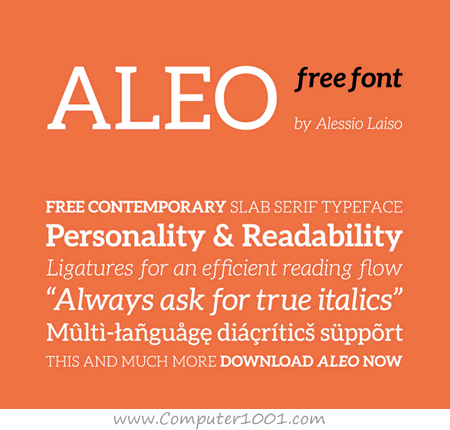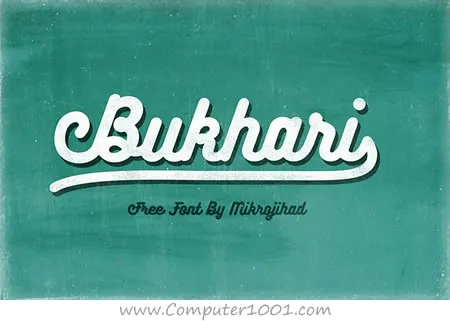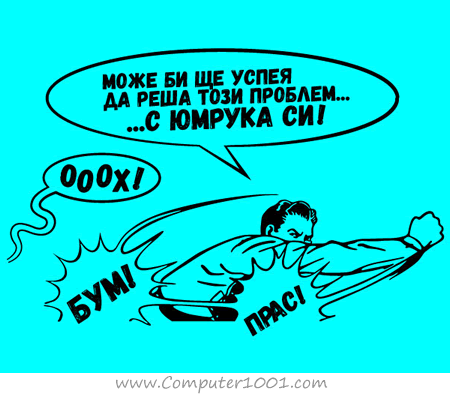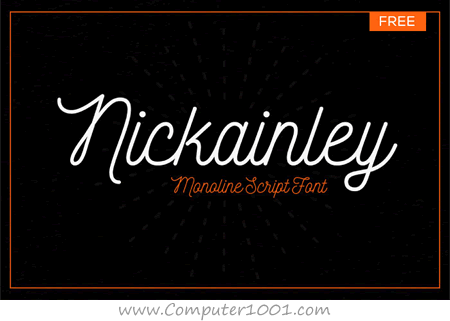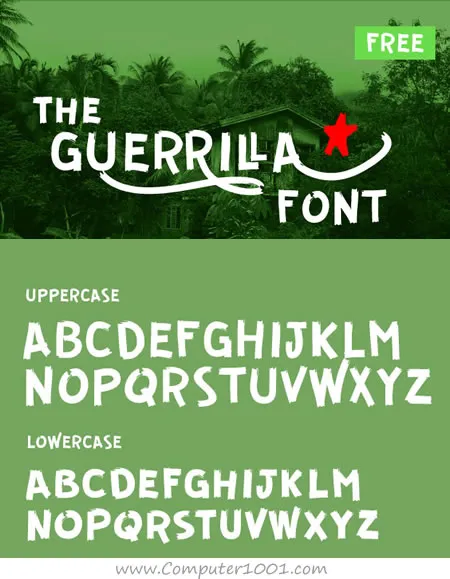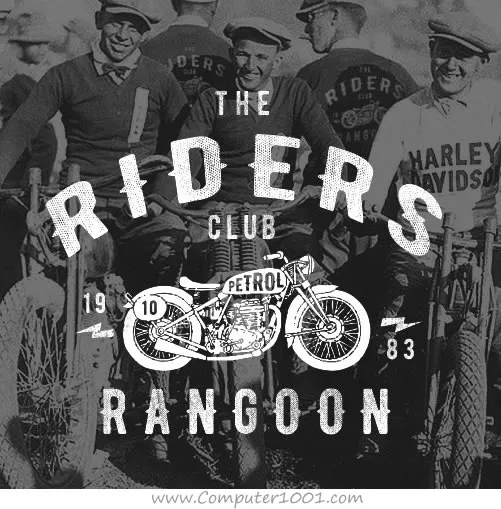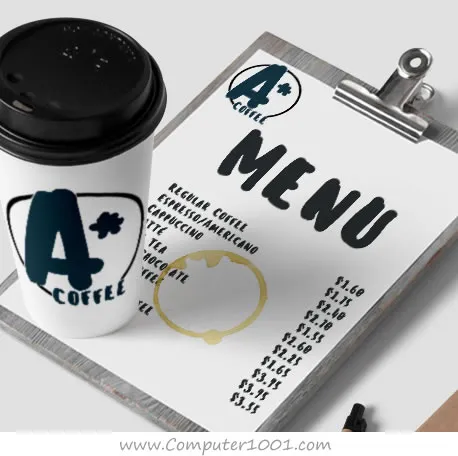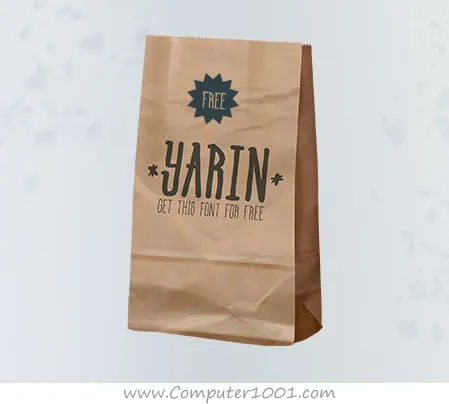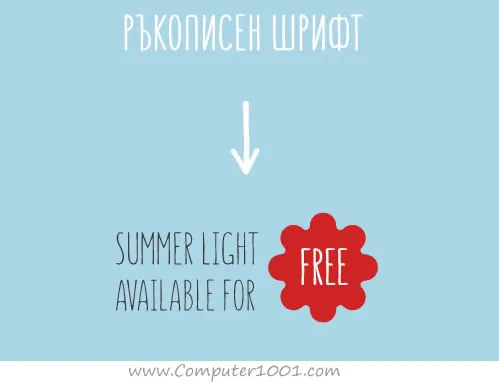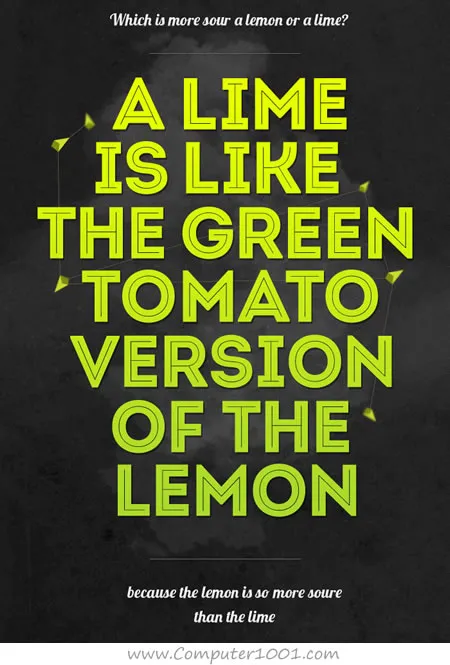
Font yang bagus dan gratis terus bermunculan, seperti 42 font yang disajikan di artikel ini.
- Aleo
- Bukhari Script
Font script yang sangat sesuai untuk berbagai desain web atau cetak, seperti logo, poster, badge, kartu nama, kaos, dan lain-lain.
- Gagalin Free Font
Ini font yang biasanya digunakan di komik-komik dan juga sesuai untuk digunakan pada desain poster.
- Nickainley
Nickainley adalah font yang bergaya klasik dan vintage. Bisa digunakan untuk desain logo, badge, kartu undangan, t-shirt, kop surat, label, poster, newsletter, dan lain-lain.
- Guerrilla
Font ini memiliki desain yang agak kasar, seperti goresan kuas, dan aksen grafiti.
- Berniers
Font huruf kapital dengan 3 gaya: Regular, Distressed dan Shade. Font ini memiliki nuansa vintage yang sesuai untuk desain badge, logo, atau desain tipografi lainnya.
- Nexa Rust
Ada 5 font gratis. Font ini memiliki desain tampilan yang agak kasar.
- Sensei Font
Font aksen kuas. Sesuai namanya, font ini diinspirasi oleh gaya manga.
- Yarin
Font bergaya tulisan tangan. Bisa digunakan untuk membuat slogan, logo, presentasi, dan lain-lain.
- SUMMER Font
Font bergaya tulisan tangan. Kita bisa download gratis font Summer Light.
- Intro
- Intro Rust
Ada 5 font gratis pada font family ini yang bisa kita download. Font bisa kita gunakan untuk desain kartu ucapan, desain packaging, atau lainnya.
- Sant’Elia Font
Ada 5 font gratis, yaitu: Rough Line (3 ketebalan), Script Bold dan Rough Alt Bold.
- GOGOIA
Desain font ini diinspirasi oleh buah-buahan dari Brazil.
- Muller Font
Font family ini cocok untuk desain apa saja, mulai dari iklan, packaging, editorial dan branding, sampai dengan proyek web. Dua font (Thin dan ExtraBold) bisa di-download gratis.
- Arkhip Font
- Blogger Sans
Font ini didesain untuk digunakan pada headline di website. Ada 8 font gratis yang bisa kita download.
- Kontanter
- Perfograma
Font unik berbentuk titik-titik.
- Panton
Ada 4 font gratis yang diberikan. Font ini sesuai untuk proyek desain web, cetak, motion graphics, t-shirt, poster, dan logo.
- Sunday Font
Font ini sesuai untuk desain packaging dan kartu ucapan.
- PH Free Font
Ada 4 font gratis.
- Rafale
Font ini sesuai untuk desain title, headline dan poster.
- Donau
Font gratis berbentuk huruf besar semuanya.
- Disclaimer
- Glober
Font sans serif untuk desain web, print, motion graphic, kaos, dan desain lain seperti poster dan logo.
- Canter
Font ini juga berbentuk huruf besar semuanya.
- Braxton
- Track
Font yang semuanya berbentuk alfabet dan huruf besar. Desainernya (Gumpita Rahayu) yang berasal dari Indonesia mendesain font ini untuk desain headline berita, poster, judul dan lain-lain.
- Lovelo Font
Font sans serif dengan aksen dua garis.
- Kelson Sans
Font dengan desain yang clean untuk poster.
- Myra
- KanKin
- Prime
- Multicolores
Font multi warna dalam format EPS dan AI (Illustrator) dan juga format OTF untuk warna hitam dan putih.
- Stiff Staff Font
- Tetra
Font bernuansa “old style” yang bisa kita gunakan untuk desain bergaya retro dan juga modern.
- Silverfake
- Metropolis
Font dengan dengan gaya garis double line.
- Rex
Font huruf besar. Tapi ada perbedaan antara caps dan small caps.
Kumpulan font ini bisa digunakan untuk proyek desain web, aplikasi, dan cetak; seperti: logo, poster, banner, aneka kartu (kartu ucapan, kartu undangan, kartu nama), desain packaging, serta untuk digunakan di newsletter, selebaran, label, dan slide presentasi.